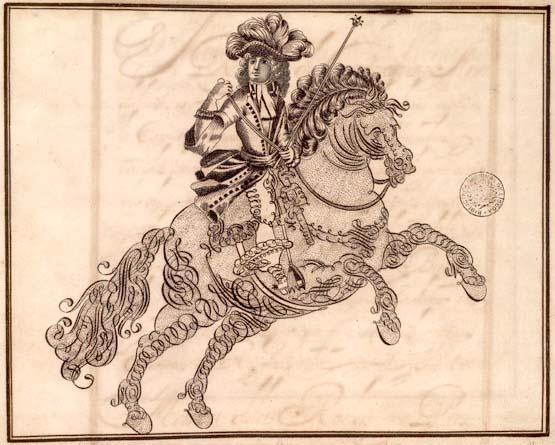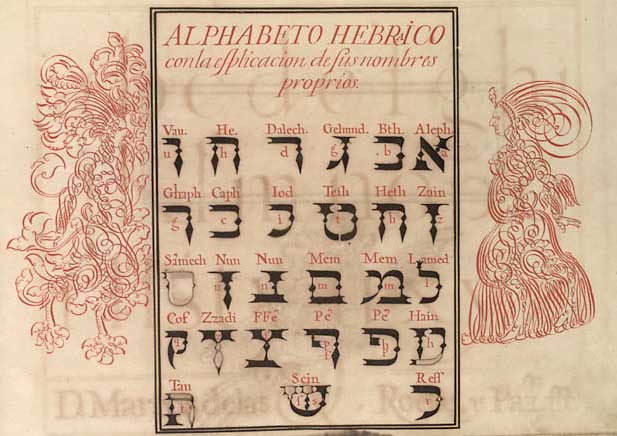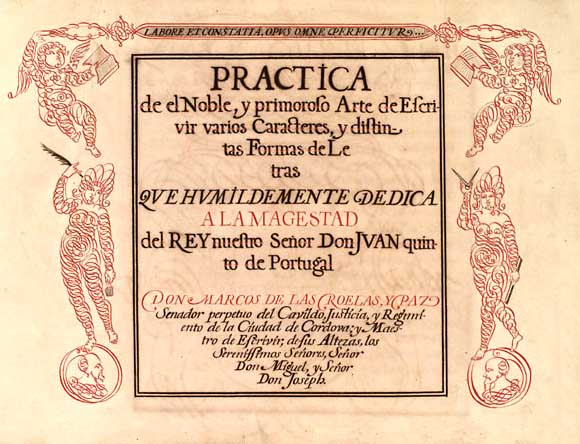
Marcos de las Ruelas y PazCalígrafo espanhol, activo na segunda década do séc. XVIII. Na corte real de Lisboa ensinou caligrafia aos filhos de João V.Arte de Escrivir, 1718-1727A obra saliente deste maestro de escrivir, a Pratica de el noble, y primoroso Arte de Escrivir varios caracteres, y distintas formas de letras, foi elaborada entre 1718 e 1727. Note-se que a igualmente importante obra de Manuel de Andrade foi elaborada em 1722. Para além deste códice, existe ainda um outro manuscrito, conservado em Madrid e datado de 1727, igualmente dedicado à arte da escrita. Foi oferecido pelo autor ao infante D. Fernando, Príncipe das Astúrias (1713-1759), futuro rei D. Fernando VI de Espanha.
A data de 1718 está patente em diversos fólios do códice, bem como o nome de Roelas y Paz como autor da letra e do desenho, que executou na corte real de Lisboa, onde ensinou caligrafia aos filhos de João V. As ilustrações cercaduras, tarjas e figuras antropomórficas, zoomórficas ou vegetalistas são quase todas de tipo caligráfico. No f. 1, desenho à pena do escudo das armas reais de Portugal, ladeado por dois guerreiros com lanças; no rosto, cercadura com dois anjos, dois medalhões e duas figuras humanas, uma com a pena e a outra com o compasso e a régua; ao longo do códice há numerosas capitais com decoração caligráfica e reproduzem-se diversos tipos de letra e caligrafia. Alguns dos desenhos são desdobráveis: custódia com Santíssimo Sacramento e Nossa Senhora da Conceição (f. 8); Rainha de Portugal (f. 9); Cristo com coroa de espinhos (f. 16); S. Francisco de Assis ajoelhado diante do Crucifixo (f. 18); infante Manuel a cavalo (f. 24); João V a cavalo (f. 29); Maria Madalena (f. 34); o Autor a cavalo (f. 40). Encadernado com pastas de cartão revestidas a pele vermelha, gravada com ferros a ouro, e super-libros com as armas reais portuguesas; corte gravado e dourado. |